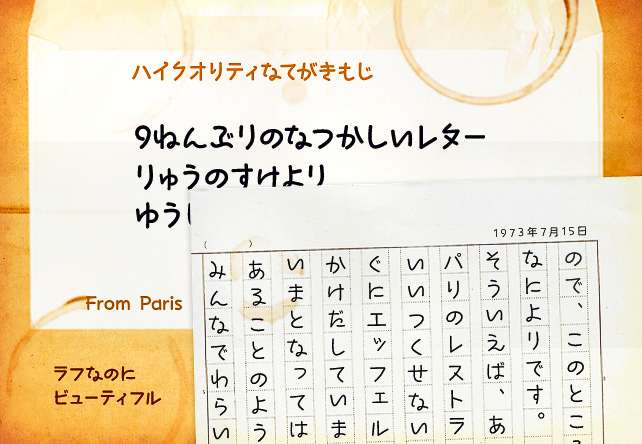
手書き風日本語フォントRyunosuke(りゅうのすけ)フォントとは りゅうのすけは男性のラフな手書き文字を参考にして作成した書体です。ラフな勢いがあるのにビューティフルな統一感のあるフォント。そして、どこか懐かしくて人なつっこい印象。ひらがな、カタカナ、アルファベット、記号のみの書体ですが、一般的な丸ゴシックの漢字と組み合わせて使える、最適な線の太さになっています。  |